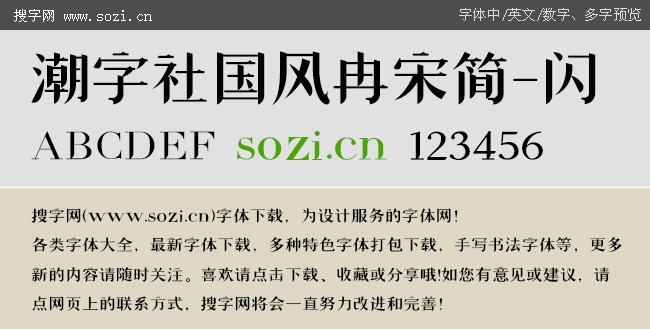
潮字社國風(fēng)冉宋簡-閃
搜字網(wǎng)提供一款潮字社國風(fēng)冉宋簡-閃中文字體下載,潮字社國風(fēng)冉宋簡融合了古典與現(xiàn)代的視覺表現(xiàn),呈現(xiàn)出新國風(fēng)的一種表達(dá)方式。這款字最大特點(diǎn)是銳而趨圓、彎則連勾、張馳有度,整體散發(fā)出一種韻律感,使字體結(jié)構(gòu)自然、灑脫、儒雅還有一點(diǎn)點(diǎn)小可愛。,可用于出版和印刷,文學(xué)雜志,海報(bào)設(shè)計(jì)等應(yīng)用。(本字體為個人非商用版,商用請聯(lián)系作者購買授權(quán))